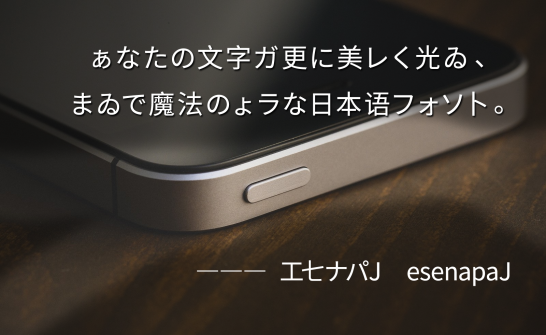
『エセナパJ』とは
『エセナパJ』(esenapaJ)は、いわゆる【中華フォント風表現ができるジョークフォント】です。
Adobe Systems Incorporatedが開発したオープンソースのOpenTypeフォント『Source Han Sans Traditional Chinese Regular(思源黑體)』をもとに作成しています。
※『Source Han Sans Traditional Chinese Regular(思源黑體)』は、日本で有名な『Source Han Sans Japanese(源ノ角ゴシック)』の、中国語(繁体字)バージョンにあたるフォントです。
日本語漢字を中国語の漢字字形で表示したり、かな文字をあえて誤字で表示したりしますので、真面目な目的での使用はご遠慮ください。
使用例
あなたのテキストに『エセナパJ』を設定すれば、さらに魅力的なタイポグラフィに進化させることができます。
デスクを離れた同僚のWordに、そっと『エセナパJ』を設定。きっと素敵なサプライズになることでしょう。 (注意・過度のサプライズは貴方の人間関係を壊す恐れがあります。)
もしかして:あなたは秘密組織の諜報員ではありませんか? 機密文書に『エセナパJ』を設定すれば、ショルダーハッキングの防止にも役立つことでしょう。